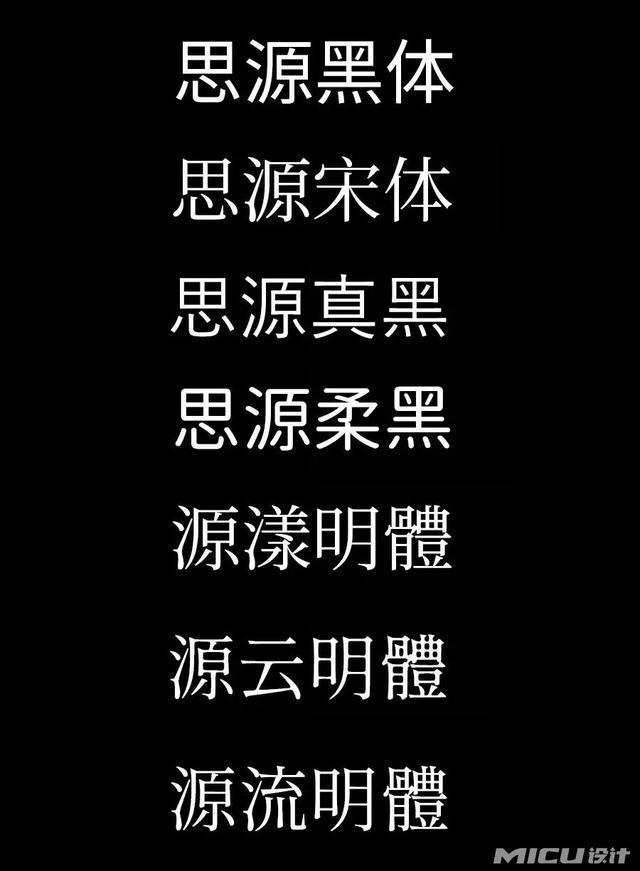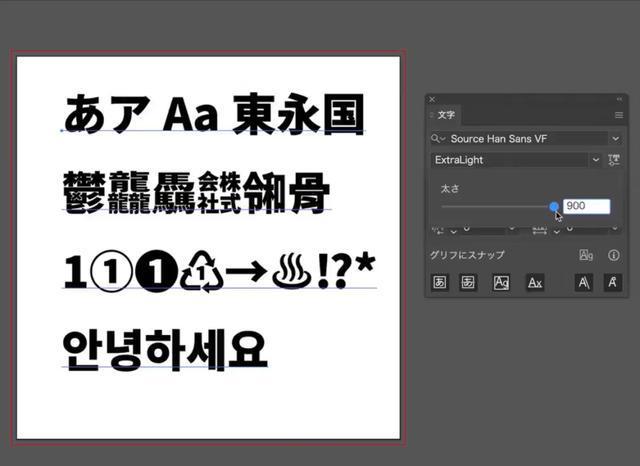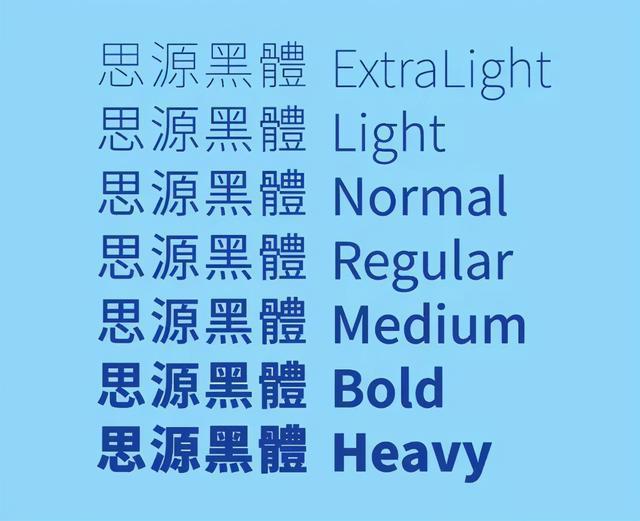
说到好看又免费的中文字体,
大家一定都会不约而同的想到思源黑体
思源字体是由Google与Adobe
联合制作的开源字体,
这款字体共有 7 个不同粗细的版本,
字体包含ExtraLight 、 Normal、 Medium、
Regular 、Bold 、Heavy七款字体粗细,
涵盖44,666个字符分属于65,535个字形中
字符数量极大,在设计界应用十分广泛。
最近,思源黑体正式更新啦!
版本升级到2.003,
字体版权年份也更新为“2014-2021”
这一次的版本升级
不仅对部分字形进行了修复及优化
最大的亮点就是
将思源黑体字形构建为
可变字体(Variable Font)
在系统或软件的支持下
升级版本思源黑体的粗细可以随意调节
具体可控制在250—900以内
你可以选取粗细值来进行控制
除此之外
思源黑体在新版本中
连笔画也可供拆分
不过目前思源黑体只
支持字重维度的形态变化,
类似字宽、字高、倾角、倒角、衬线等
维度还无法实现自由变换。
提到方正字体总是让设计师望而却步
不过其中也不乏有可以商用的字体
方正黑体、方正仿宋、方正书宋和方正楷体
这四款字体是可以商业使用的
但值得一提的是使用时需要方正公司书面授权
国内有名的字体设计师胡晓波
推出的3款免费商用
胡晓波真帅体、男神体、骚包体
三款别具特点的字体
适用于海报设计、电商设计等。
问藏书房体
问藏书房字体
是造字工房联合“问藏书房”
精心打造的一款免费可商用字体品牌字体
共收容字数6864CJK汉字,
ASCII常用字符100个
整体现代简约,中宫紧凑,
视觉阅读极具层次感,
字字俊秀且呈现古雅之风
王汉宗字体系列
字体由中原大学数学系
王汉宗教授研发设计
但由于一些字体字形与汉仪字库
产生版权纠纷建议大家谨慎使用
以下三款为未产生纠纷的字体
台北黑体
台北黑体 (Taipei Sans TC) 是
由「翰字铸造」2019 年新推出的一款字体,
适用于文字排版、平面设计、影音字幕
以及平面印刷类的设计使用,
而且是免费个人及商业用途。
破产字体-Fandol
这个名字是不是很奇葩,
不过据说是由于母公司破产
而后改为免费商用字体
庞门正道字体
庞门正道发布的三款免费字体,
三款字体拥有独特且明显的特征
可广泛应用于包装及电商设计。